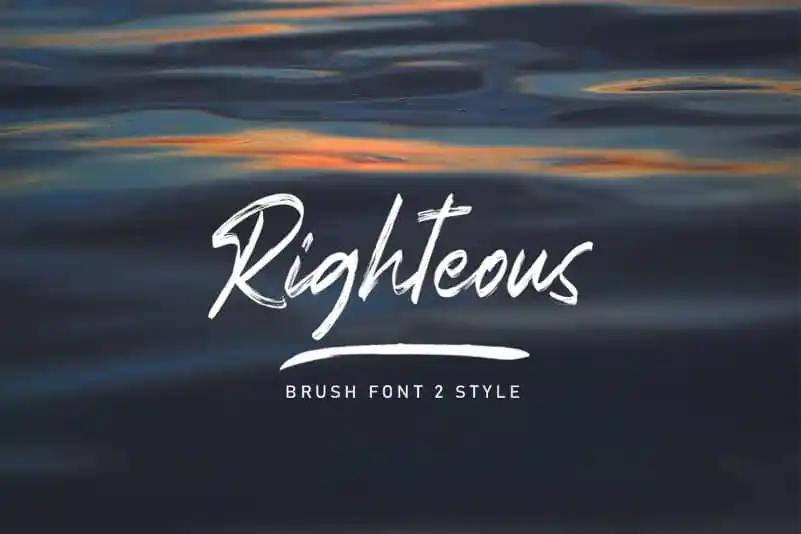
Righteous Brush Font – Download Grátis
A Righteous Brush Font é uma fonte script inspirada nos estilos de grafite, moderna e retro-moderna, com linhas limpas de canvaço que proporcionam um toque autêntico e único para seus projetos digitais. Ideal para marcas, logotipos, designs de casamento, posts em mídia social, anúncios, embalagens de produtos, design de produtos, etiquetas, fotografia, marca d’água, convites, material de estação, e qualquer projeto que seja beneficiado por uma escrita a mão. Com seu design robusto e contemporâneo, a Righteous Brush Font se destaca como um recurso indispensável para designers digitais atentos ao detalhe e às tendências dos dias atuais.